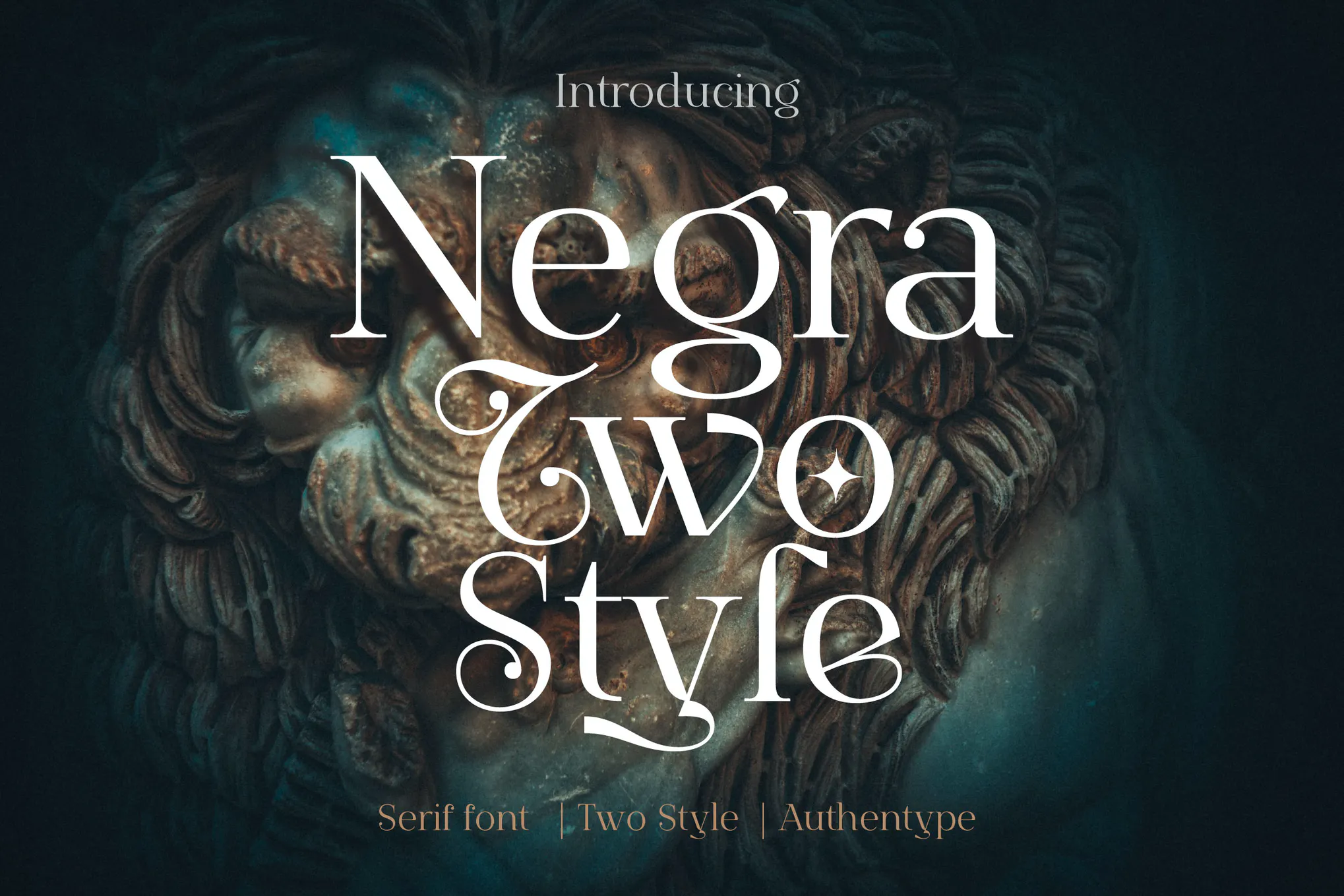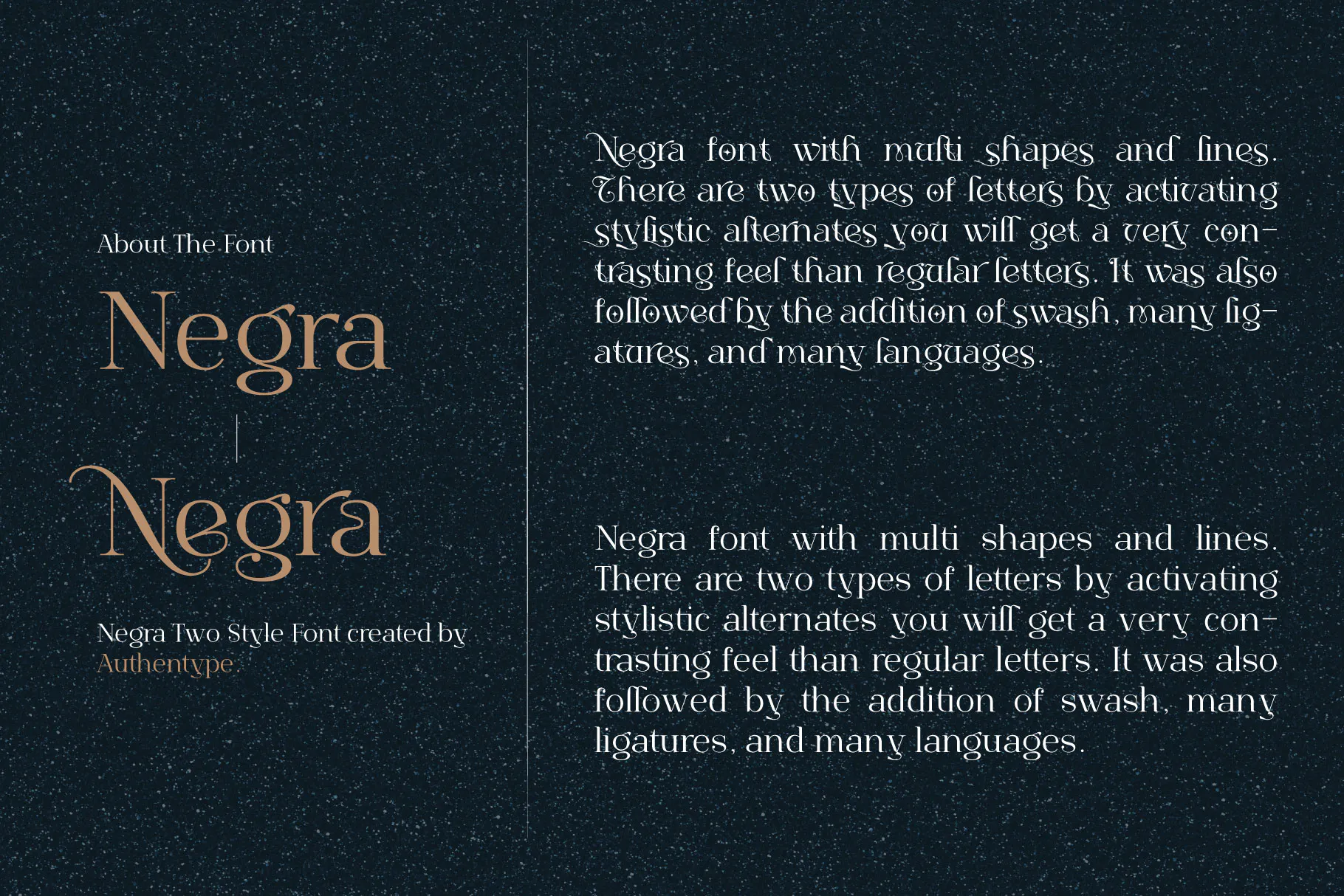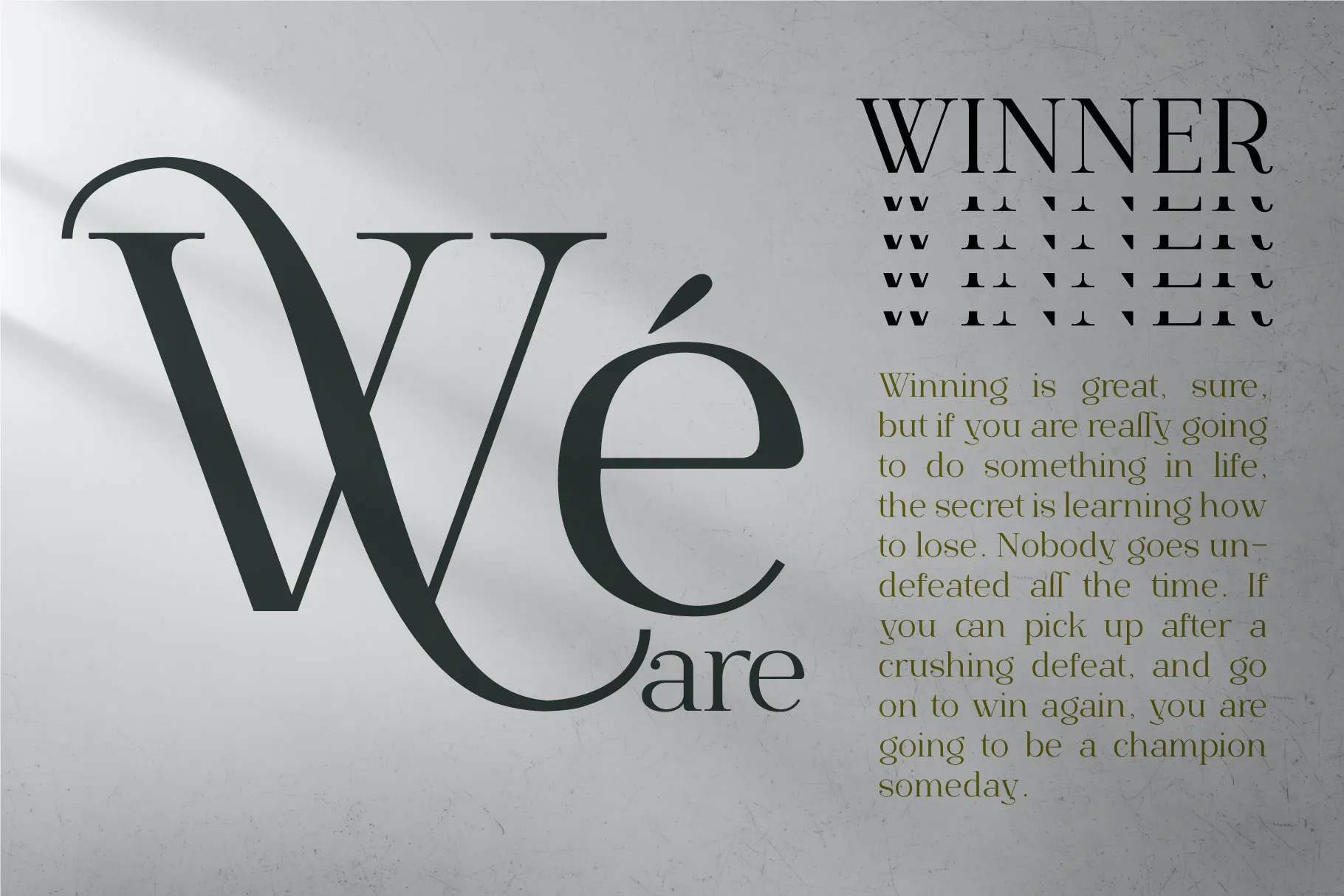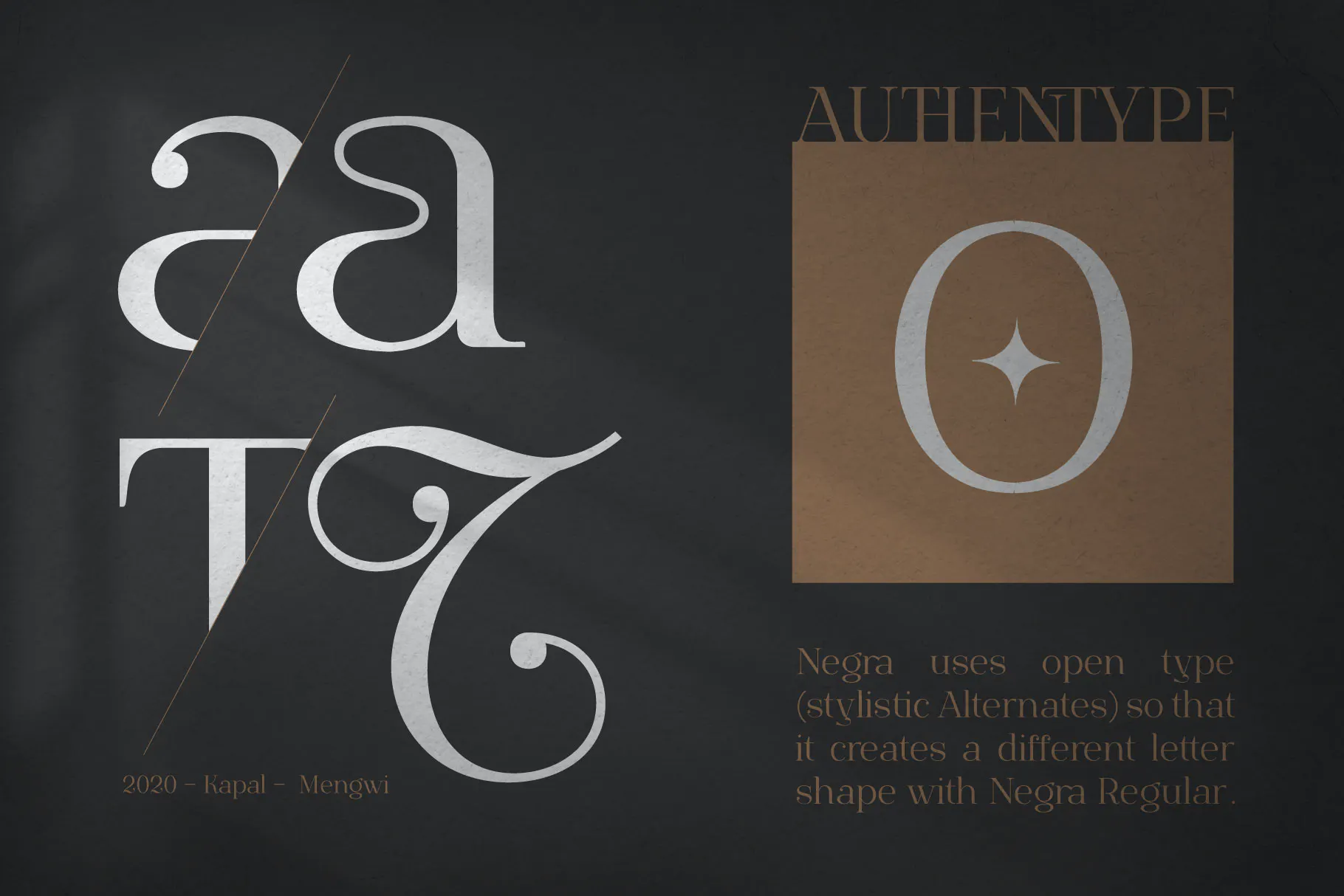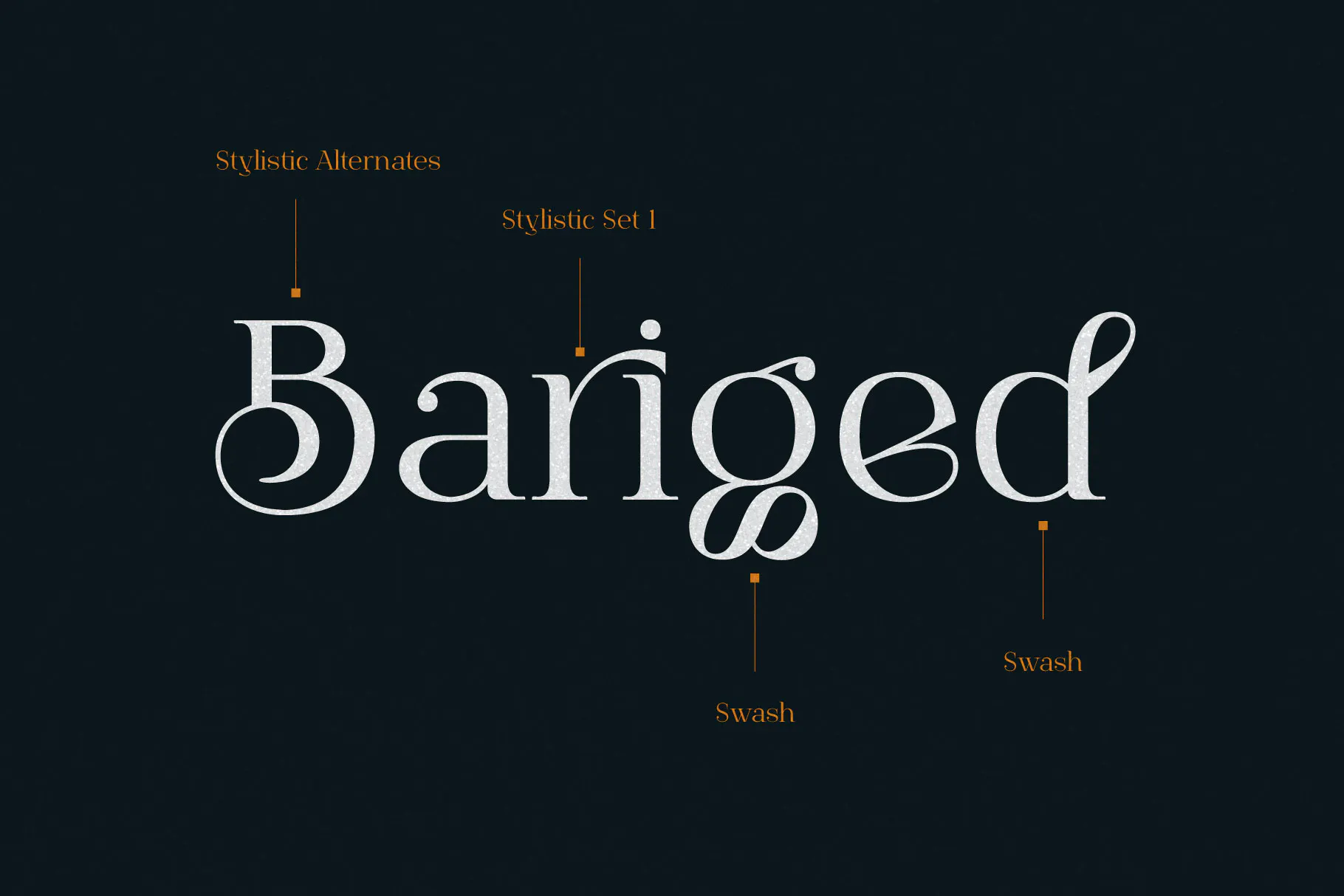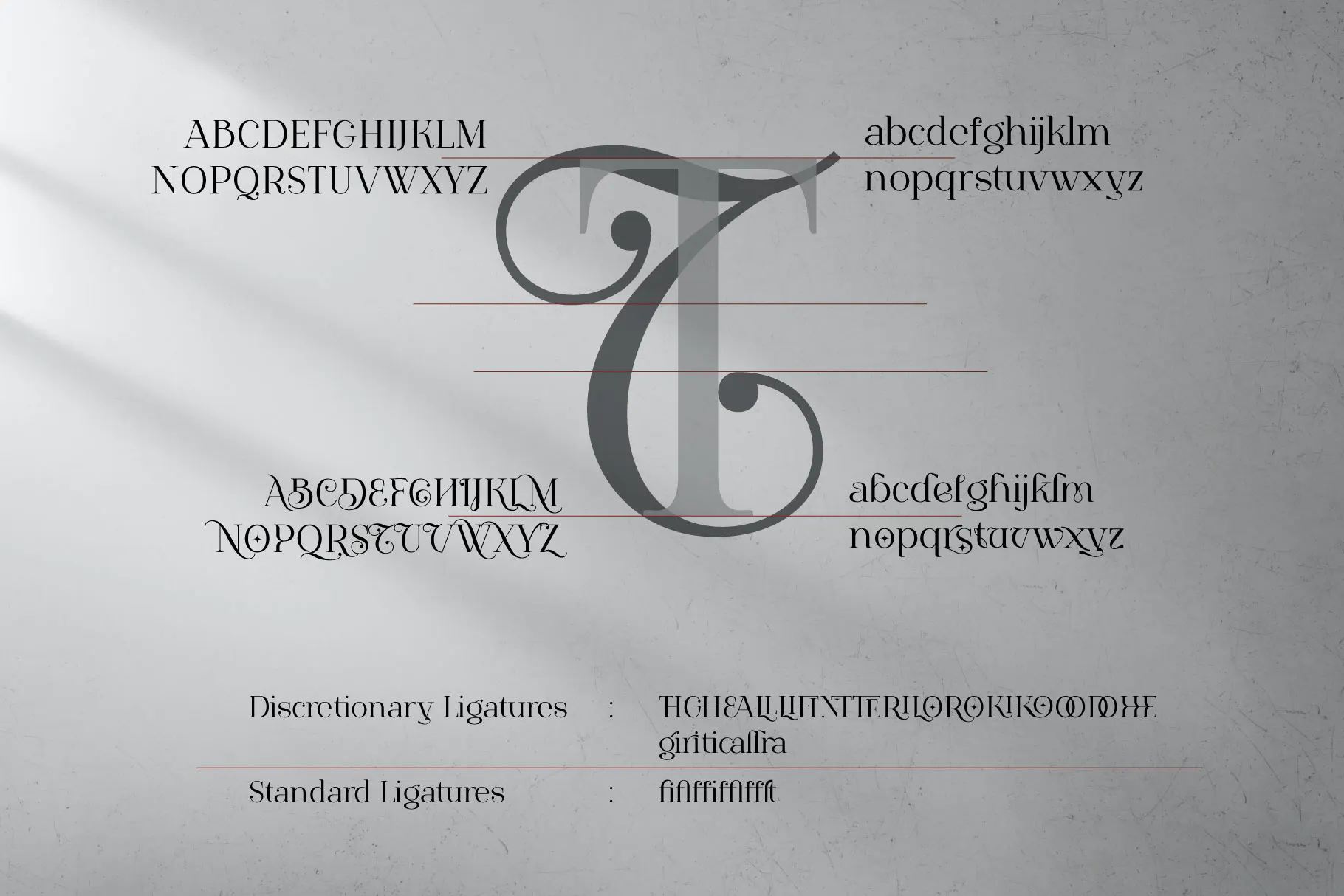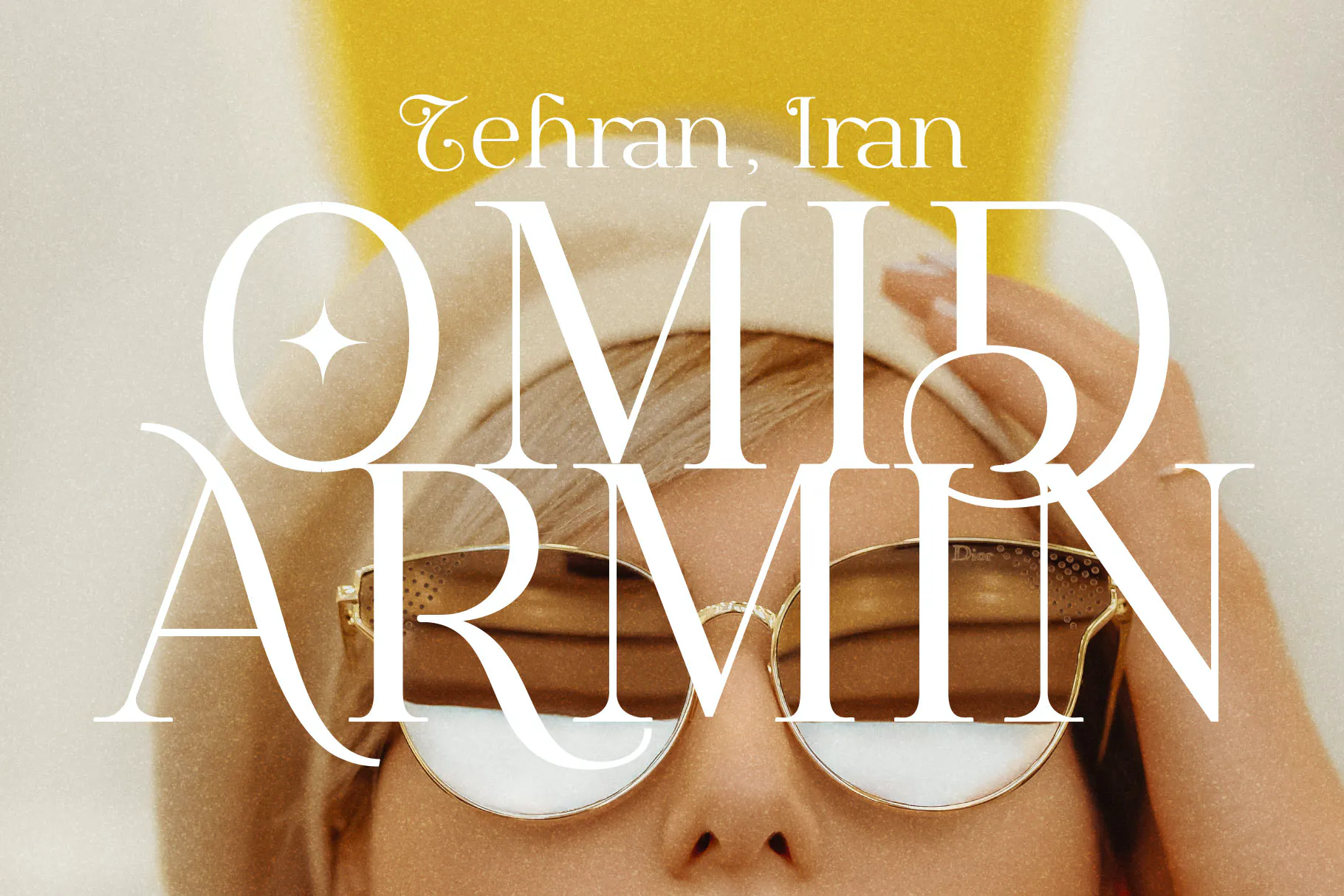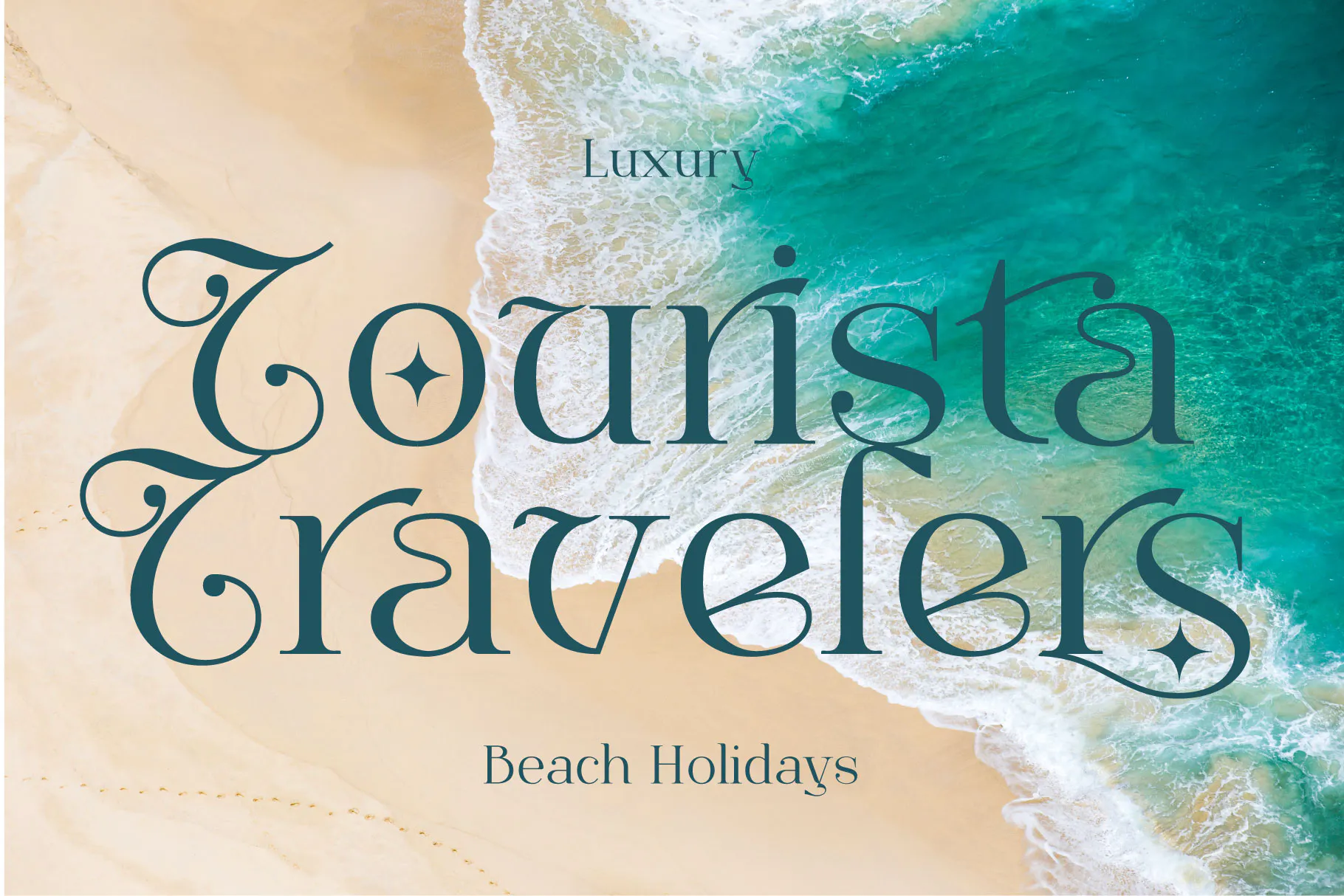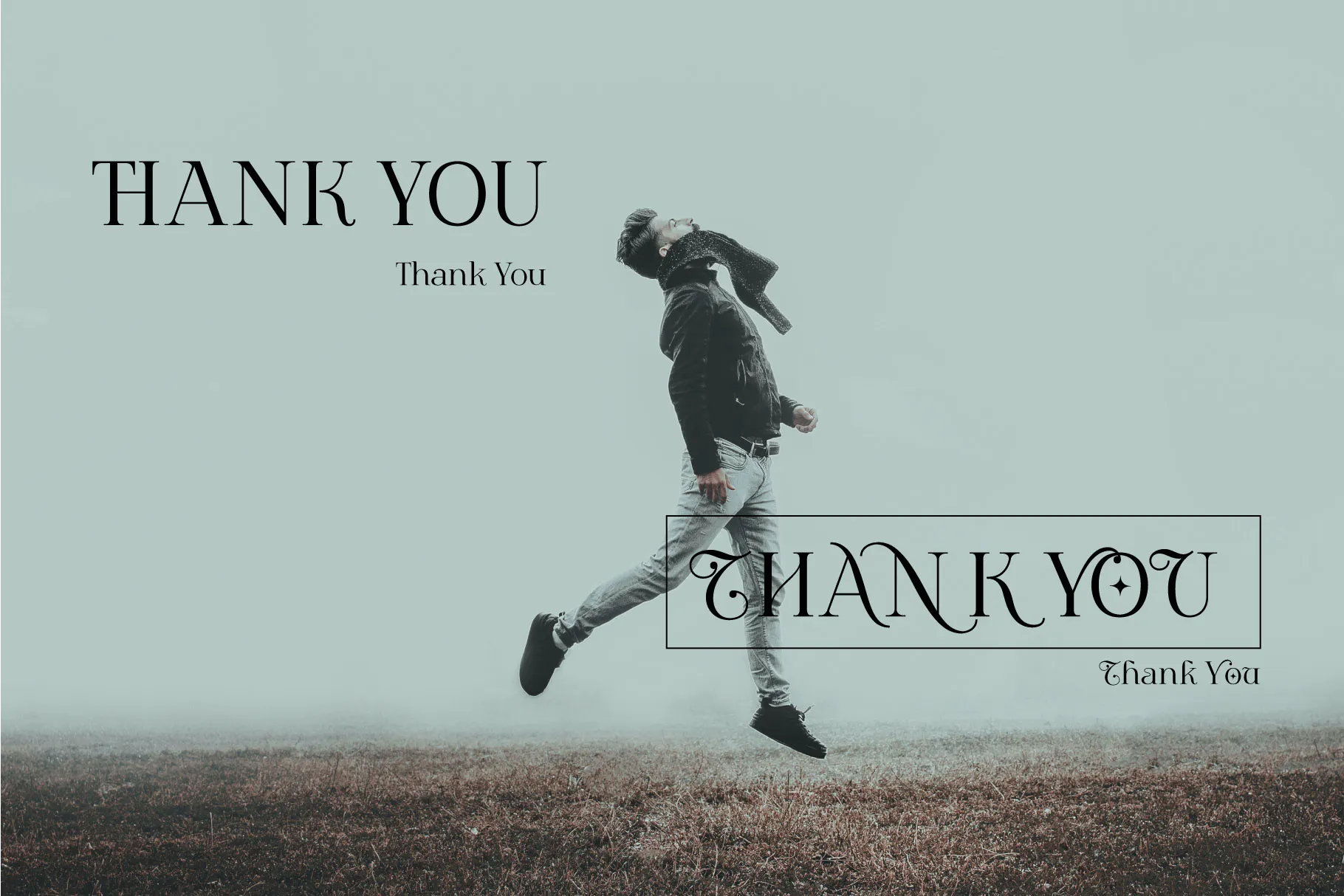
Negra – فونت دو سبک با چند شکل و خطوط. دو نوع حروف وجود دارد که با فعال کردن جایگزین های سبک، احساس بسیار متضادی نسبت به حروف معمولی خواهید داشت. همچنین به دنبال آن اسواش، بسیاری از لیگاتورها و بسیاری از زبان ها اضافه شد.